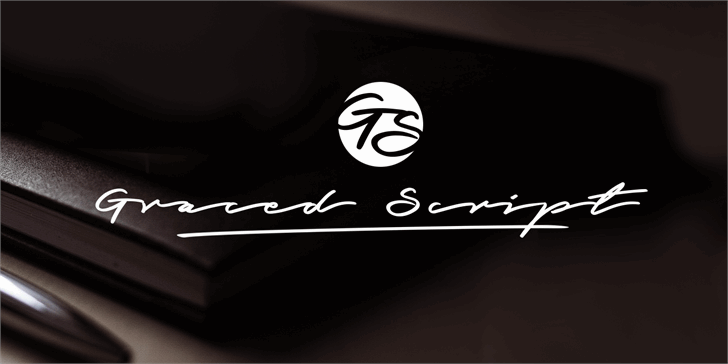
Graced Script Font – Download Grátis
Descubra a elegância do Graced Script Font, uma fonte escrita à mão criada pelo designer Hamilton. Com traços suaves e linhas finas, essa fonte oferece um toque sofisticado para textos legíveis e atraentes. Suave como o riso da chuva ao se despedir do outono, ou o canto dos pássaros acordando a manhã, Graced Script é perfeita para adicionar um toque delicado e personalizado aos seus designs. Seja em logotipos ou pequenos detalhes, essa fonte escrita à mão convidativa é uma escolha inteligente que não apenas faz seu design se destacar, mas também o torna único. Visite www.mansgreback.com/graced-script para adquirir sua própria licença comercial e desfrutar dessa delicadeza na prática de seus projetos.